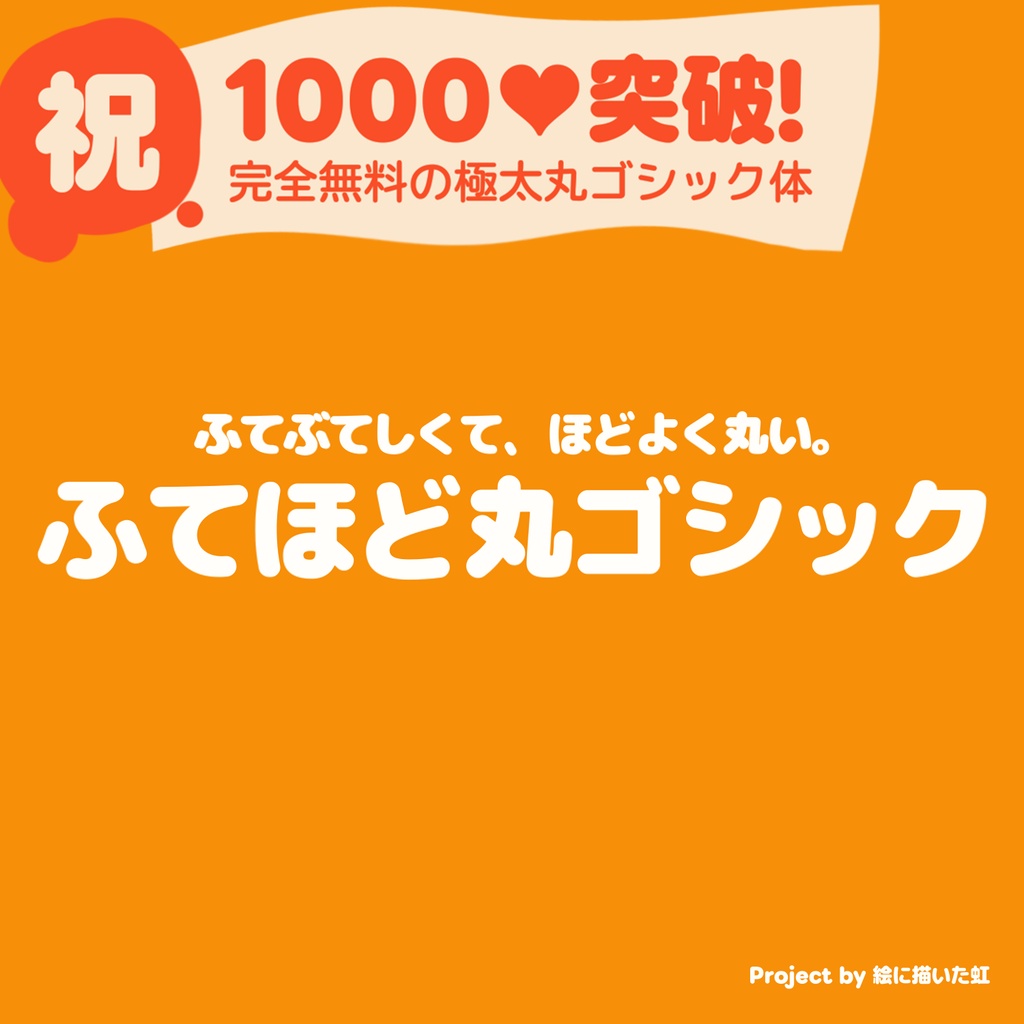
【フリーフォント】ふてほど丸ゴシック
細いウエイトをお求めの方はこちら https://infiniterainbow.booth.pm/items/8752124 完全フリーの極太丸ゴシック体です。 商用利用もご自由に。 SIL Open Font License 1.1のもとで改変・再配布も可能です。 スペシャルサンクス - ポプらむ☆キウイ - 自家製 Rounded M+ [2025.12.23]ver1.01 「豪」の字が「壕」と表示されていたため代用フォントで置き換え [2025.02.13]ver1.02 TTFではなくOTFファイルになっていたのを修正 [2026.05.14]ver1.03 Microsoft Wordにて日本語フォントとして選択できなくなっていた問題を修正 [2026.08.02]ver1.04 旧字体・簡体字に関する字形置換設定を削除し、macOSにて「紬」が「絣」と表示されるなどの問題に対応。 [2026.08.10]ver1.10 ライセンス表示および予約フォント名を整理し、OFL.txt・MPLUS-FONT-LICENSE.txtなどの関連文書を同梱。フォント内部のライセンス情報と埋め込み設定も修正。